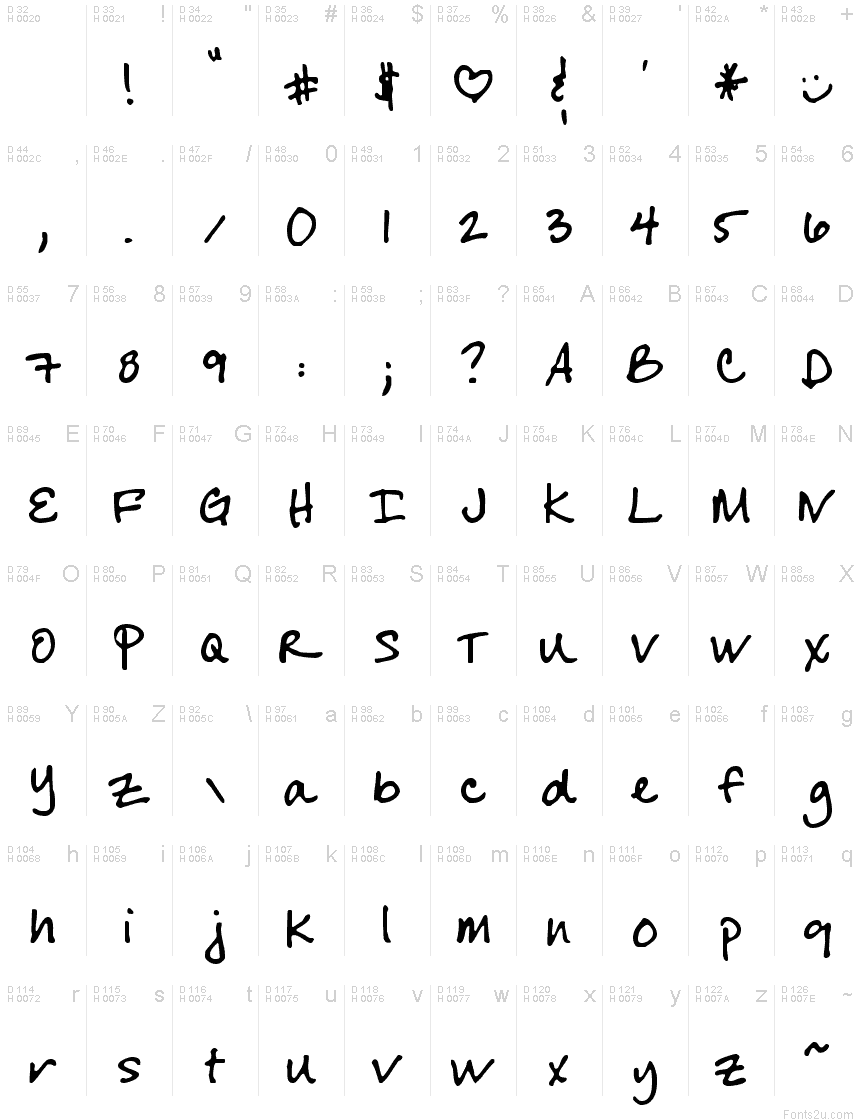
Písmo Cheryl od autorky Ellinor Rapp je bezplatný font, který zachycuje pocit tlustého, inkoustem nasáklého fixu klouzajícího po papíře. Písmena jsou uvolněná, zaoblená a trochu hravá, takže všemu, co napíšete, dodají vřelý a osobní nádech – jako by to byla rychlá poznámka na lednici nebo štítek na oblíbené dóze. Font si udržuje stálý rytmus, takže i přes svůj ležérní půvab zůstává text snadno čitelný.
Cheryl skvěle vynikne na přáních, dětských plakátech, v hlavičkách diářů, na kartičkách s recepty, samolepkách a stylových obalech. Nejlépe vypadá ve střední až větší velikosti, kde opravdu vyniknou její robustní tahy a hravé křivky. Pokud hledáte jednoduchou kombinaci, zkuste použít Cheryl na nadpisy a doplňte ji čistým bezpatkovým písmem pro menší text – výsledek bude působit přátelsky a přehledně.